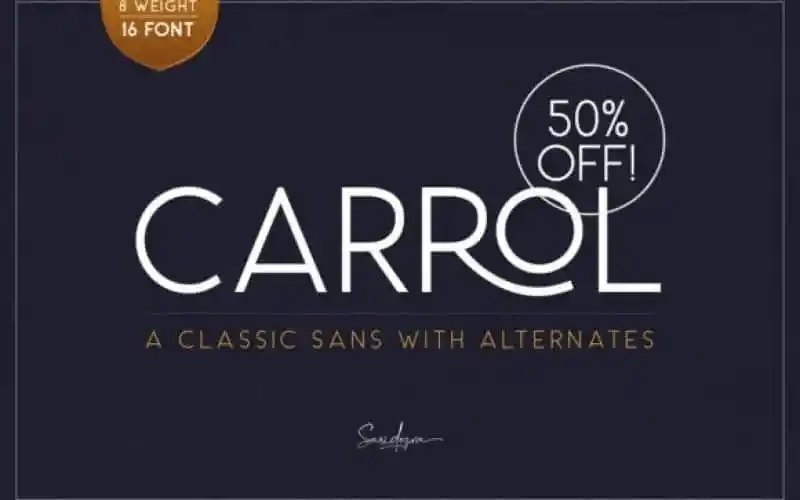
A Carrol Sans Serif é uma elegante tipografia sem serif que se destaca por sua coragem estética e energia juvenil. Ideal para a geração millennial, esta fonte cativante encontra seu uso ideal entre as agências digitais e criativas. Ela se adequa perfeitamente ao público jovem graças à sua versatilidade inigualável: pode ser usada tanto em títulos quanto em logomarcas, citações ou até mesmo como fonte complementar a uma tipografia serifada. O seu grande diferencial é o suporte a múltiplas línguas, oferecendo inúmeros alternativos para cada letra do alfabeto, atendendo às necessidades de qualquer projeto multilingue. Ideal tanto para uso pessoal quanto para projetos profissionais, essa fonte é uma ótima escolha para quem busca elegância e modernidade em sua identidade visual.